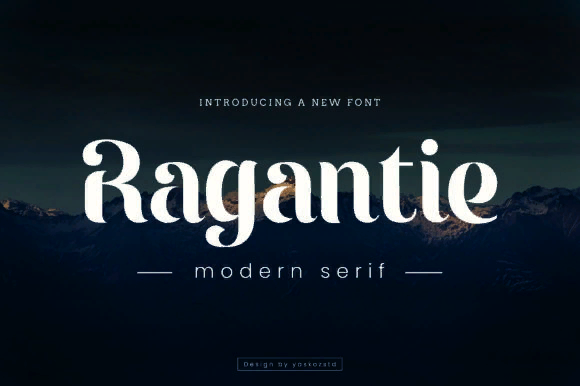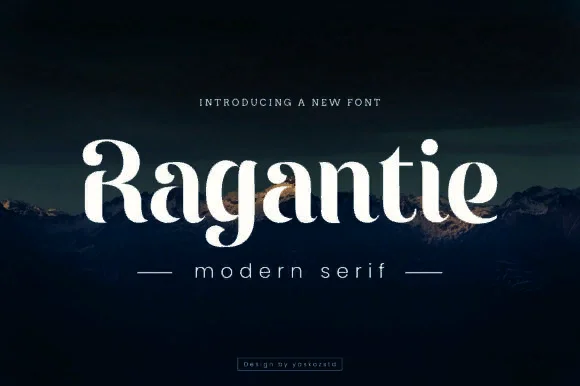
Название: Ragantie Font (2021)
Ragantie - классный, смелый и толстый шрифт с засечками.
Независимо от темы, этот шрифт станет отличным дополнением к вашей библиотеке шрифтов, поскольку он способен возвысить любое творение.